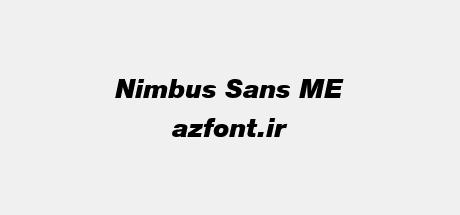
Nimbus Sans ME
فونت زیبای رایگان Nimbus Sans ME
قلم زیبای Nimbus Sans ME Black Italic از سری قلم های بسیار زیبا برای تایپوگرافی و لوگو تایپ می باشد.این قلم در وزن Black Italic و توسط www. toolps.blogspot.com طراحی و منتشر شده است.